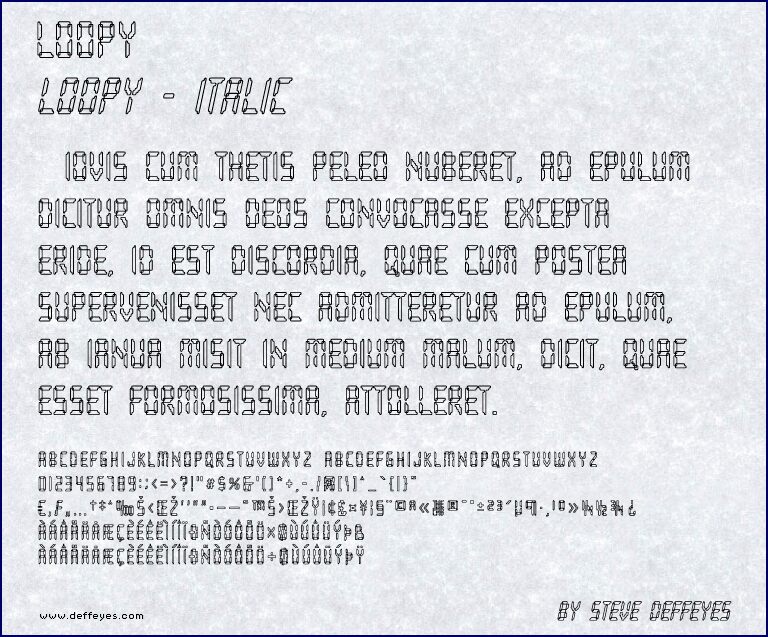
Loopy Italic autorstwa Steve'a Deffeyesa to darmowy font cyfrowy typu display o konturowych, zapętlonych kształtach, które wyglądają, jakby były złożone z zaokrąglonych prostokątnych segmentów. Litery i formy powtarzają rurową strukturę z kanciastymi łączeniami i otwartymi światłami wewnątrz liter, co nadaje krojowi mechaniczny, arcade'owy rytm.
Loopy Italic świetnie sprawdza się w tytułach na plakatach, logotypach, okładkach albumów, ulotkach i grafikach technologicznych, gdzie rysunkowy styl inspirowany ekranami jest na miejscu. Oszczędny kontur i segmentowa konstrukcja pasują również do akcentów na opakowaniach, oznakowaniach i krótkich podpisach redakcyjnych, które potrzebują wyrazistego cyfrowego charakteru bez zbędnych dekoracji.
Jest, cóż, loopy!